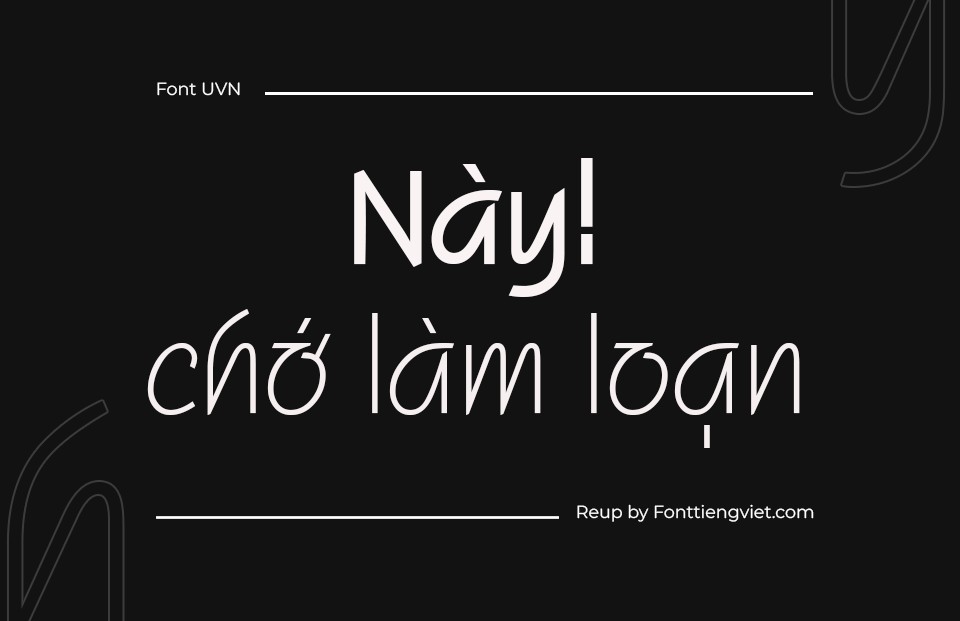
Giới thiệu về Font Việt Hóa UVN Giay Trang
Trong thế giới thiết kế đồ họa dành cho trường học, việc tìm kiếm một bộ Font Chữ phù hợp là vô cùng quan trọng. Font Việt Hóa UVN Giay Trang nổi lên như một lựa chọn hàng đầu nhờ phong cách nhẹ nhàng và thanh lịch. Đây là phông chữ thuộc bộ UVN nổi tiếng, được tối ưu hóa hoàn toàn cho bảng mã Unicode, giúp người dùng gõ tiếng Việt có dấu một cách chính xác mà không lo bị lỗi hiển thị. Với đường nét mô phỏng chữ viết tay tự nhiên trên những trang giấy trắng, bộ font này mang lại cảm giác gần gũi và đầy hoài niệm cho mọi tác phẩm.
Ưu điểm nổi bật của Font Việt Hóa UVN Giay Trang
Đặc điểm lớn nhất của Font Việt Hóa UVN Giay Trang chính là sự mềm mại và rõ ràng. Khác với các phông chữ nghệ thuật quá cầu kỳ, UVN Giay Trang giữ được sự cân bằng giữa tính thẩm mỹ và khả năng đọc hiểu. Điều này giúp các thầy cô giáo dễ dàng soạn thảo giáo án điện tử hoặc trình chiếu bài giảng mà vẫn thu hút được sự chú ý của học sinh. Ngoài ra, font cũng rất nhẹ, tương thích tốt với các phần mềm phổ biến như Microsoft Word, PowerPoint hay Photoshop.
Ứng dụng thực tế của phông chữ trong học đường
Bộ Font Việt Hóa UVN Giay Trang thường được sử dụng rộng rãi trong việc thiết kế thiệp mời họp phụ huynh, làm bằng khen cho học sinh hoặc trang trí bảng tin lớp học. Sự tinh tế của nó giúp các văn bản hành chính bớt đi vẻ khô cứng, thay vào đó là sự chân thành và trang trọng. Các bạn học sinh cũng có thể dùng phông chữ này để làm báo tường hoặc trang trí sổ tay cá nhân thêm phần sinh động.